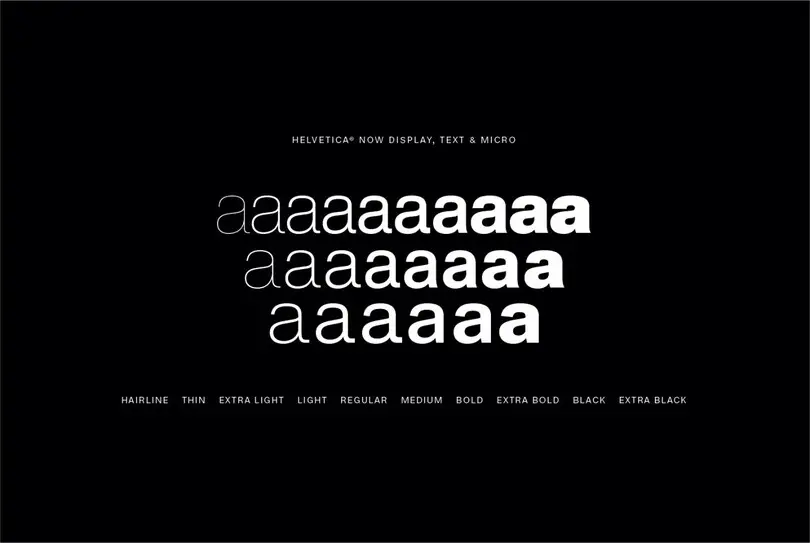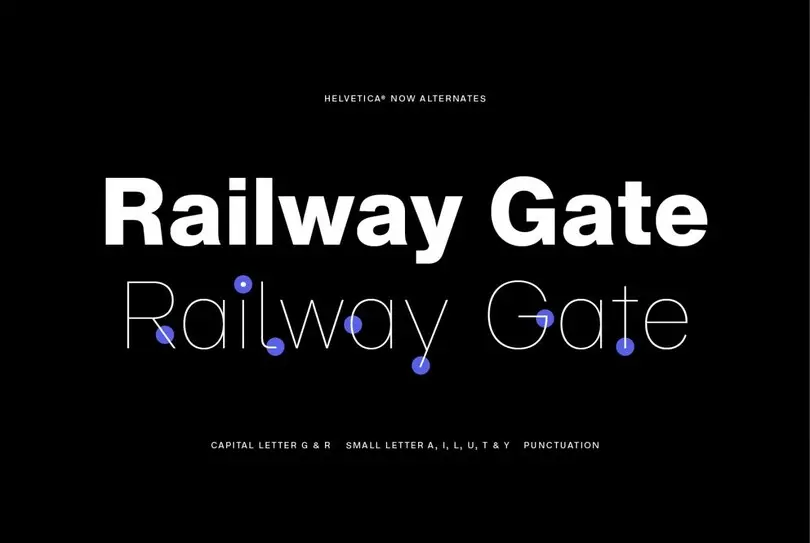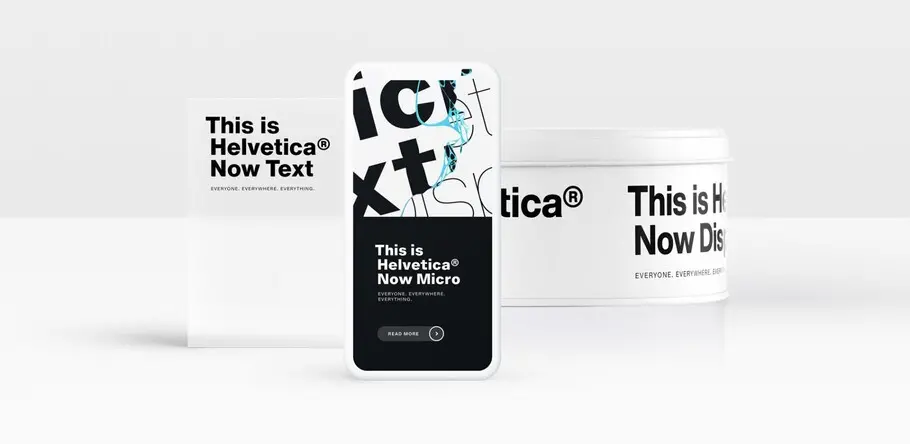
Von Neue zu Now: Wie Helvetica ins 21. Jahrhundert einzog
„ Das Designerteam von Monotype hat beliebte Verbesserungen eingebaut, die im Laufe der Jahre an der Schrift vorgenommen wurden.“ “
Sechs Jahrzehnte sind seit der Geburt von Helvetica vergangen, und bis heute ist die Familie für viele die erste Wahl, wenn es um klare und neutrale Typografie geht. Gleichwohl sind die Anforderungen an diese Schrift – und das gilt für viele Klassiker – in den letzten beiden Jahrzehnten enorm gestiegen. Die legendäre Schweizer Sachlichkeit von Helvetica muss sich heute in einer Vielzahl von Umgebungen und einem breiten Spektrum von Textgrößen entfalten, was zuletzt nicht immer perfekt gelang.
Viele Designer und Agenturen haben sich mit der Neuen Helvetica arrangiert, die 1983 herauskam. Doch sie ist ein Kind des analogen Zeitalters. Hier sind vier Gründe, warum der Moment gekommen ist, zur digital geborenen Helvetica Now zu wechseln.
Die Größen
Helvetica Now bietet erstmals optischen Größen, nämlich Mikro, Text und Display, die eigens für Kleingedrucktes, Lesetexte und Headlines entwickelt wurden … während die Neue Helvetica vor allem für die Nutzung als Textschrift gezeichnet und spationiert wurde. Wer Plakate und Leitsysteme entwickelt wird sich über die neue Display-Version freuen, die für das Setzen großer Texte spationiert wurde: eine lupenreine Helvetica, aber mit mehr Souveränität und Sicherheit, und dem Potenzial für Experimente und Individualisierung (durch Alternativzeichen). Wer sich mit der Lesbarkeit von Mengensatz beschäftigt, egal ob gedruckt oder digital, kann sich auf Helvetica Now Text freuen, ein Arbeitstier, mit robuster Architektur und großzügigen Metriken.
„ Wer Plakate und Leitsysteme entwickelt wird sich über die neue Display-Version freuen, die für das Setzen großer Texte spationiert wurde.“ “
Die Micro-Version stellt eine herausragende neue Eigenschaft von Helvetica dar und löst ein Problem, dem die Schrift seit langem hilflos gegenüber stand: Kleingedrucktes. Während Neue Helvetica bei kleinen Textgrößen an ihre Grenzen kommt, seien es Fußnoten, Tabellen oder Fließtext auf einem Tablet, läuft die Micro hier zu Hochform auf. Einfache Lettern mit teils übertriebenen Details erhalten das Helvetica-Schriftbild im Bereich von 4 bis 8 Punkt, während die große Mittellänge und eine geräumige Spatinierung die Lesbarkeit bei mikroskopischen Größen und/oder bei niedrigauflösenden Umgebungen gewährleistet.
Helvetica Now offers Micro, Text and Display sizes, each of which is tailored to a particular environment—unlike Neue Helvetica, which was drawn and spaced for use in text type.
Die drei optischen Größen wurden konsequent unter Berücksichtigung der späteren Nutzung entwickelt und exakt auf die hier gültigen Anforderungen abgestimmt. Das bedeutet für die Benutzer, anders als zu Zeiten von Neuer Helvetica, dass alle Schnitte sofort gebrauchsfertig sind, ohne manuelle Eingriffe oder typografische Tricks.
Die Zeichenpalette
Helvetica Now wurde als kompletter Werkzeugkasten konzipiert, der es erlaubt, die ausdrucksstarke Seite des Schriftklassikers abzurufen. Darüber hinaus bietet die Schrift in allen Schnitten eine Reihe optionaler Alternativzeichen, die der Klarheit des Designs folgen und es den Benutzern trotzdem erlauben, dem Helvetica-Schriftbild eine individuelle Tönung zu geben.
Sonderzeichen und Symbole erweitern die Einsatzgebiete von Helvetica, zum Beispiel positive und negative eingekreiste Ziffern oder die zur Helvetica passenden Pfeile, die man sich früher von anderen Schriften ausleihen oder zusätzlich erstellen musste. Die über 800 Zeichen sind in allen Helvetica Now Strichstärken und -Stilen enthalten und verleihen der Familie ein ungeahnte Flexibilität und Einsatzvielfalt.
Alternate forms of key glyphs—like a single-story a—have been added across the entire range.
Die Details
Helvetica Now ist mehr als eine Aktualisierung oder ein Update. Das Designteam im Monotype Studio startete zunächst mit den ursprünglichen Entwürfen, überprüfte und überarbeitete dann jedes Zeichen der Familie und fügte anschließend Modifikationen hinzu, die zum Teil bereits vor Jahrzehnten vorgenommen wurden. Altbekannte Probleme, wie der leicht mit dem Großbuchstaben I zu verwechselnde Kleinbuchstabe l, wurden mit einer (optionalen) Halbserife gelöst, die das Lesen kleinerer Texte verbessert. Weitere Neuerungen sind ein aktualisiertes @, runde Akzente und Satzzeichen, ein G ohne Abstrich, ein R mit geradem Bein, das geschlossene a und der Kleinbuchstabe u ohne Abstrich … alle optional einstellbar und kombinierbar.
„ Das Designerteam von Monotype hat beliebte Verbesserungen eingebaut, die im Laufe der Jahre an der Schrift vorgenommen wurden.“ “
Obwohl jede Erweiterung einen größeren Nutzen bringt, verglichen mit den Vorgängern, stellt Helvetica Now gleichwohl eine Rückkehr zum ursprünglichen Ethos und Geist von Helvetica dar. Das Designteam von Monotype unterwarf sich bei der Neugestaltung einer strengen Selbstverpflichtung mit dem Ziel, jeden Buchstaben nur so zu verfeinern, dass er der Klarheit, Einfachheit und Neutralität von Helvetica mehr dient als schadet.
„Wenn man Helvetica Now mit den ursprünglichen Entwürfen vergleicht, ist sie um eine Klasse besser lesbar, was viel weniger mit den Buchstabenformen als mit deren Zurichtung zu tun hat.« betont der Monotype Type Director Charles Nix. »Tatsächlich ging es vor allem darum, die Räume zwischen den Buchstaben zu studieren und herauszufinden, nach welcher Methodik sie früher funktionierten, wie sie der Schrift ihre Qualität gaben, dies dann zu reproduzieren und dort mit den Verbesserungen anzusetzen.“